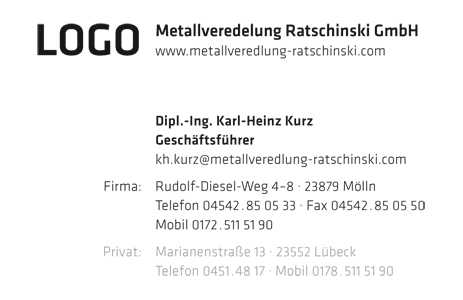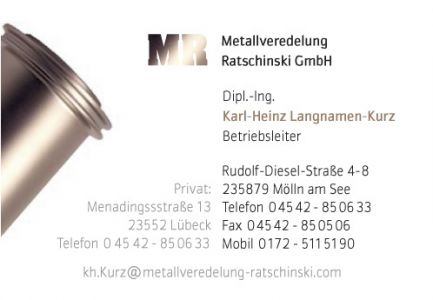
guter versuch, gefällt mir.
wobei ich auf das abgesetzte grau verzichten würde, dazu noch ein
paar tabs und das ganze wirkt ruhiger. das grau würde ich maximal,
wenn überhaupt bei der privaten adresse verwenden.
die adresse oben ist von der idee her nicht dumm, auch wenn mich die linien stören würden (ggf. den ganzen block negativ, wie die webadresse?) diese würde notfalls auch noch in die mitte passen, sind ja nur 2 zeilen. aber es zum firmennamen zu schreiben ist nicht verkehrt.
auf jedenfall gefällt mir die größere schriftgröße, jedenfalls wirkts sie größer im vergleich zu den beispielen von sandra.
Na herrlich, dass ich auch mal was anschauen darf. Ich bin gespannt, wann RM mit seiner Variante rausrückt. Ich glaube, eine schöne Karte kann es mit soviel text nicht geben. Oder?
Der Versuch von Wladimir wäre mir zu bunt. Toll find ich aber, wie du die Webadresse verstaut hast. Mail-Adresse trennen, das habe ich nicht gewagt, da dachte ich, fällt der RM über mich her.
Auf die Schrift habe ich bei meinem Entwurf gar nicht geschaut, ich wollte ja nur eine grobe Ideen-Skizze machen. Man kann mit Schriften doch viel verändern, aber die Idee muss erstmal passen.
RM, unsere Designer bauen nie was nach, in unserer Firma heisst es immer: ganz oder gar nicht. Erst mal wird der kunde von allem befreit, was er mitbringt ;-) Oder er geht woandershin.
Dass du deine karte nicht zeigst - völlig okay, ich zeige meine ja auch nicht. Aber was du mit deiner vorgabe anfängst, das interessiert mich wirklich. Du scheinst Erfahrung zu haben bei Karten mit mit viel Text. Aber vielleicht gibt es noch Skizzen von anderen?
wenn ich einen Kunden hätte, der unbedingt soviel Text auf seine Visitenkarte packen will.. nun gut:
Dann würde ich ihm eine Klappkarte vorschlagen.
Hochformat und nicht genau auf Mitte gefalzt, sondern
etwa 3 mm nach links versetzt, so daß im unteren Teil diese 3 mm hervorblitzen. Und die würde ich dann farbig im Anschnitt drucken.
So hätte ich die Möglichkeit, den Text zu teilen und gleichzeitig den automatisch "geringwertigeren" Text auf der Innenseite durch den 3 mm Farbrand wieder zum gleichwertigen Part aufzuwerten.
Joh.. so würde ich das machen.
passt doch alles problemlos drauf!
hab bewusst auf typodetails, flächen und farben verzichtet um nur
mal die rein info zu zeigen. die kleine typo hat 7,5 pt, die größere 9 pt -
die karte ist standard (85 x 55 mm) ...
Auch schön :!: Der »Verlauf« nach unten gefällt mir gut.
und dem kunden gleich noch ein neues Logo verkauft ;)
Prima! Einwände: Würde mir besser gefallen, wenn ich nicht die Kreditkarte so scheusslich finden würde, also das Format. Und die Web-Adresse ist doch nicht Bestandteil des Firmennamens, oder doch? Denn wenn du die Zeile unten unterbringen willst, wird es eng. Aber die Zäune hab ich mir selber gebaut. ich finde den Entwurf von allen bislang am besten.
Vom Betriebsleiter ist Herr kurz jetzt zum Geschätsführer aufgestiegen, auch schön!
Ach so: Klappkarten - never ever!! Nix für Pinnwände und Visitenkartenbücher und Karteikästen und zum Aufkleben. Nur privat halbwegs okay.
Prima! Einwände: Würde mir besser gefallen, wenn ich nicht die Kreditkarte so scheusslich finden würde, also das Format.
fuer das beispiel habe ich bewusst auf ein spezielles format verzichtet.
ich persoenlich wuerde immer eher "schlanke" visitenkarten bevorzugen
und ein extremeres format waehlen.
Und die Web-Adresse ist doch nicht Bestandteil des Firmennamens, oder doch? Denn wenn du die Zeile unten unterbringen willst, wird es eng.
ich denke die website ist heute weit wichtiger als adresse und telefon.
deshalb auch die positionierung direkt beim firmenschriftzug. zur not
wuerde die zeile aber auch noch unten passen. das ganze ist ja auch nur
eine trockenuebung gewesen ...
perfekt! vorallem die idee die mailadresse unter den namen zu setzten.
den titel könnte man notfalls über den namen setzten, bin kein freund von
titel vor dem namen, aber das wäre ja kein problem. platz ist ja da.
die webadresse hätte ich auch unter den firmennamen gesetzt. das haben
wir bei den vk von unserem kunden damals auch so gestaltet. vorallem
fällt sie dort auf, und das sollte sie ja auch. die mobilnummer zu wieder-
holen ist außerdem ein schöner trick um harmonie zu schaffen.
Uff, jetzt habe so lange rumgebastelt und "microboy" kommt mir zuvor. Finde ich besser als meinen Entwurf. Allderings: haut das wirklich mit der Schriftgröße hin?
Die Skizze von Mikroboy ist schon sehr gut, da gebe ich RM nochmal recht. Und die vom herrn Sharif mit der verschobenen Mittel-Achse :cry: und dem Foto - tu mir leid, das ist ein bisschen abngründig und eighty-like.